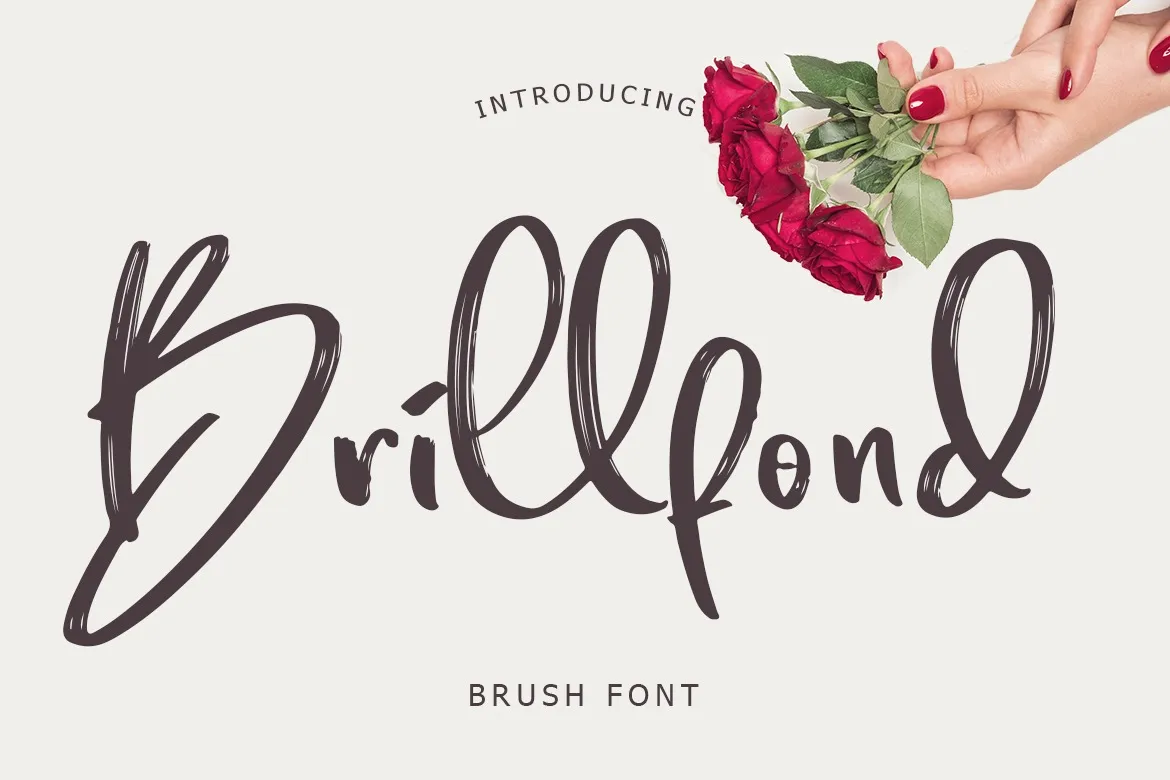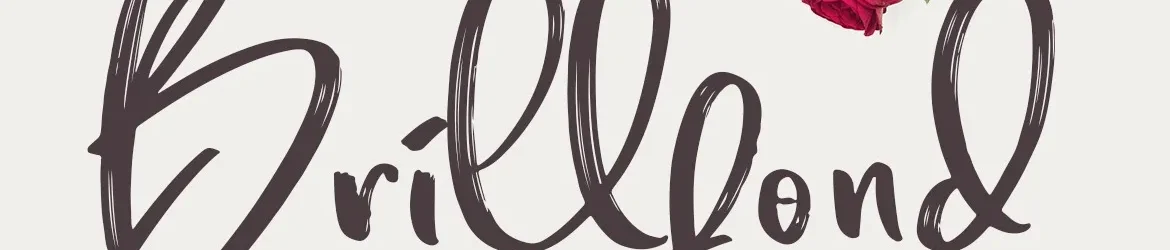
A fonte ‘Brillfond Font’ é uma elegante escolha para estilos modernos e luxuosos, criada por lyanatha em forma de letra escrita à mão com suporte à pintura. Este script font apresenta um acabamento áspero e texturizado, tornando-a perfeita para decorar seus materiais digitais. Suave o suficiente para incorporar uma personalidade única no seu layout, mas robusta o bastante para manter a leitura clara de qualquer texto que selecione. Perfecto para um design contemporâneo e sofisticado.